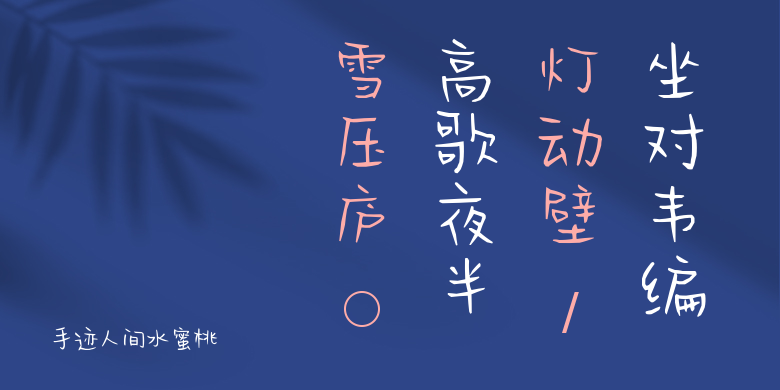
手迹人间水蜜桃
手迹人间水蜜桃,这款字体结构工整、笔画清晰,兼顾美观与易读性,适用于标题、正文、海报、包装、LOGO 等多种场景。字形优雅稳定,风格百搭耐看,适配日常排版与创意设计,让文字呈现更舒适、更具质感。手迹人间水蜜桃一笔一画,皆是细节,以均衡的比例、流畅的线条打造舒适视觉体验,字形端正大气,风格简约现代。无论是商业设计、品牌宣传还是日常排版,都能轻松驾驭,让文字更有格调与力量。手迹人间水蜜桃字体下载。